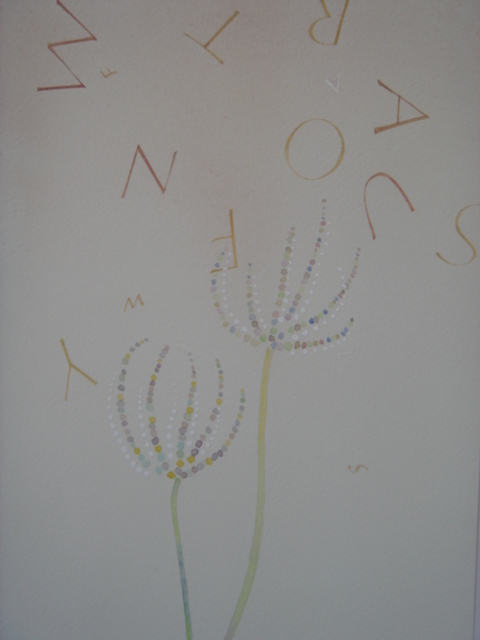
咲け咲け、飛べ飛べ!
きょうから新学期。新入生のランドセル姿がまぶしいです。
新しいスタートの日、いいなあ!
たんぽぽがあちこちに目立つようになりました。ふりそそぐ日ざしがよく似合いますね。
お気に入りだったたんぽぽ野原は工事が始まってしまいました。空き地がひとつ、またひとつと消えていく・・・
残り部分で今年もがんばって咲いてほしいです。
たんぽぽ綿毛にはまだ早いですが、アルファベットを飛ばしてみました。
以前作ってほったらかしだった紙類を片付けていたのです。書きかけた文字がひとつあって(つまり失敗したのでやめてしまった)
これは何かにならんかなあ〜と、また文字をつけたし、また一つつけたしていくうちに、なぜだかたんぽぽ綿毛になりました。
再利用も悪くないです。どこからでもスタートできるっていいですね。